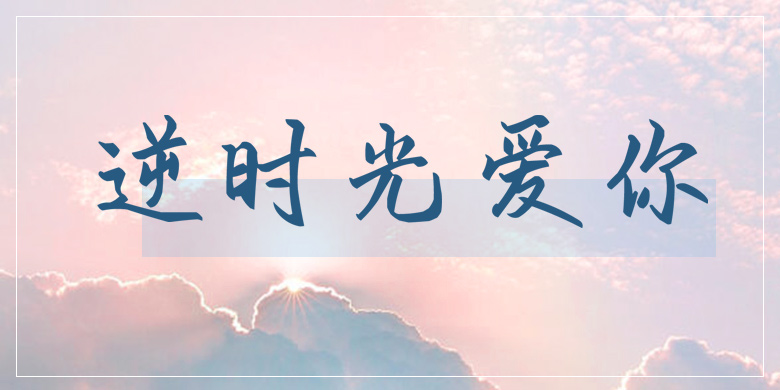
品牌:方正手迹设计师:俞亦婷发行时间:2019字库编码:简繁扩展(GBK)分类:常规书写·硬笔字体属性:精品字
逆时光爱你这款字体的笔法结构皆源自传统书法,巧妙的将传统书法与现代审美相结合,整体风格娟秀淡雅且文艺气息十足,让人赏心悦目。适用于现代诗歌、短文印刷、文艺类的书刊、品牌广告和产品包装设计、综艺影视字幕,以及社交网络的个性化用字。